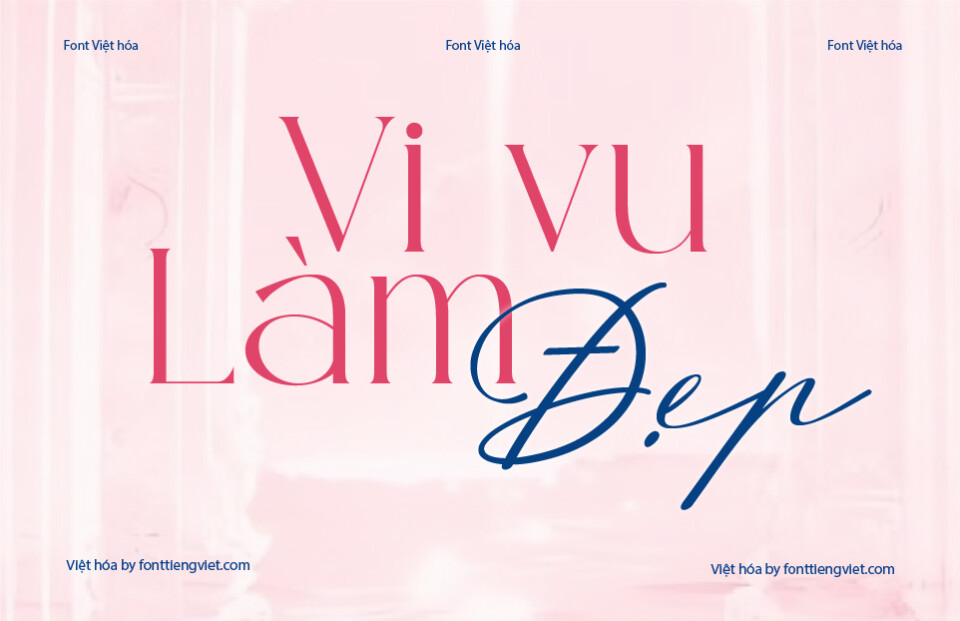
Font Việt hóa 1FTV VIP Sermo
Trong cộng đồng thiết kế đồ họa hiện nay, việc tìm kiếm một bộ Font Việt hóa 1FTV VIP Sermo chất lượng cao là điều vô cùng quan trọng để tạo nên những tác phẩm ấn tượng. Đây là một bộ Font Miễn Phí được tinh chỉnh kỹ lưỡng, giúp người dùng không còn lo lắng về lỗi hiển thị tiếng Việt hay thiếu hụt các ký tự đặc biệt. Với phong cách hiện đại, thanh lịch và mang tính ứng dụng cao, bộ font này đang trở thành lựa chọn ưu tiên cho các dự án từ thiết kế bao bì, poster quảng cáo cho đến các bài thuyết trình học đường. Sự kết hợp giữa đường nét tinh tế và khả năng truyền tải thông điệp mạnh mẽ đã giúp 1FTV VIP Sermo khẳng định vị thế trong lòng các designer Việt.
Đặc điểm nổi bật của Font Việt hóa 1FTV VIP Sermo
Bộ font này không chỉ đơn thuần là các ký tự chữ cái mà còn là một công trình nghệ thuật được đầu tư bài bản về mặt thị giác. Điểm nhấn lớn nhất chính là sự cân bằng giữa các khoảng trắng và nét chữ, tạo cảm giác dễ nhìn nhưng vẫn giữ được cá tính riêng biệt.
Tính linh hoạt trong ứng dụng thực tế
Font Việt hóa 1FTV VIP Sermo được thiết kế với nhiều định dạng khác nhau, từ nét mảnh thanh thoát đến nét đậm mạnh mẽ. Điều này cho phép người dùng linh hoạt sử dụng trong nhiều ngữ cảnh khác nhau. Ví dụ, trong môi trường giáo dục, các bạn học sinh có thể dùng bộ font này để làm tiêu đề cho các báo cáo ngoại khóa hoặc thiết kế thiệp chúc mừng thầy cô, giúp nội dung trở nên trang trọng và thu hút hơn. Đối với các nhà thiết kế chuyên nghiệp, đây là công cụ đắc lực để tạo ra bộ nhận diện thương hiệu mang đậm chất riêng.
Tối ưu hóa hiển thị trên mọi nền tảng
Một trong những lý do khiến bộ font này được yêu thích là khả năng tương thích tuyệt vời trên cả hệ điều hành Windows và macOS. Dù bạn đang sử dụng phần mềm đồ họa chuyên dụng như Photoshop, Illustrator hay đơn giản là Word và PowerPoint, 1FTV VIP Sermo đều hoạt động mượt mà, không xảy ra tình trạng lỗi dấu hay nhảy chữ. Điều này giúp quy trình làm việc trở nên thông suốt và chuyên nghiệp hơn bao giờ hết.
Cách sử dụng Font Việt hóa 1FTV VIP Sermo hiệu quả
Để phát huy tối đa vẻ đẹp của bộ font này, người dùng cần lưu ý đến cách phối hợp màu sắc và kích thước. Sự kết hợp giữa các tông màu pastel nhẹ nhàng với phông chữ này sẽ tạo ra cảm giác tinh tế, trong khi các gam màu tương phản mạnh sẽ giúp thông điệp trở nên bùng nổ và hiện đại.
Kết luận về giá trị của bộ font